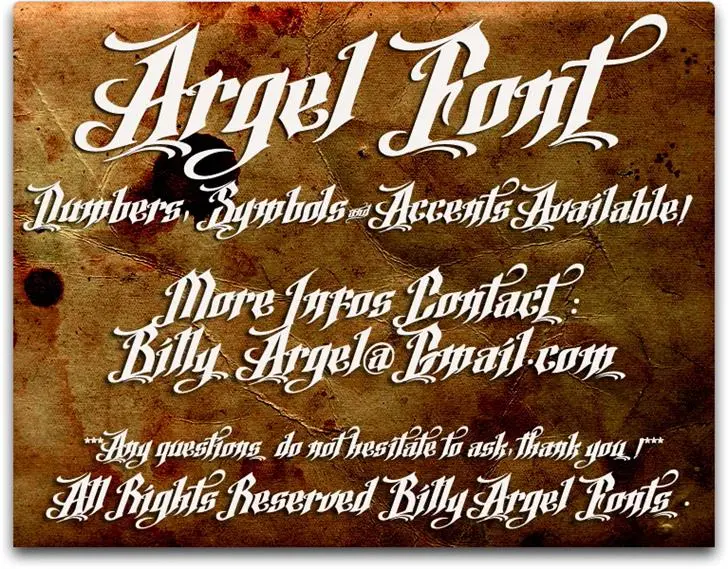
A ‘Argel Font’ é uma elegante fonte para display, perfeita para criar visuais impactantes e chamativos. Desenvolvida por Hamilton, essa fonte traz um conjunto rico de letras que inclui nomes icônicos e caracteres especiais variados. Ela é ideal para uso em identidades digitais, banners, e qualquer projeto gráfico visual que precise de uma aparição atrativa e memorável. Combinando clareza e sofisticação, a ‘Argel Font’ oferece um contraste perfeito entre as letras mais leves e os títulos mais robustos. Esta fonte é uma excelente escolha para qualquer projeto onde o design do texto deve destacar-se. Seja em projetos de marketing digital, anúncios ou até mesmo designs pessoais, a ‘Argel Font’ não só torna suas criações únicas e memoráveis, mas também as deixa com um toque moderno e profissional.